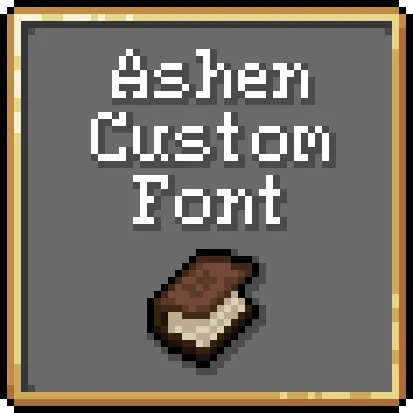
Ashen 16x Custom Font
Пользовательский средневеково-фэнтезийный шрифт 16x для Minecraft, заменяющий стандартный шрифт на новый серифный дизайн. Совместим с большинством пакетов ресурсов.
Этот шрифтовой пакет заменяет весь стандартный шрифт Minecraft на новый серифный шрифт, созданный с нуля в средневеково-фэнтезийном стиле. Он был разработан для использования с Ashen 16x, но доступен как отдельное дополнение для тех, кто хочет применять его с другими пакетами ресурсов.
Шрифт представляет собой полную гарнитуру, охватывающую не только стандартный латинский алфавит, но и алфавиты Иллагеров и Стандартный Галактический (для зачарований). Он поддерживает все символы, которые можно ввести в стандартной Minecraft, за исключением случаев, когда игра использует символы Юникода, такие как деванагари.